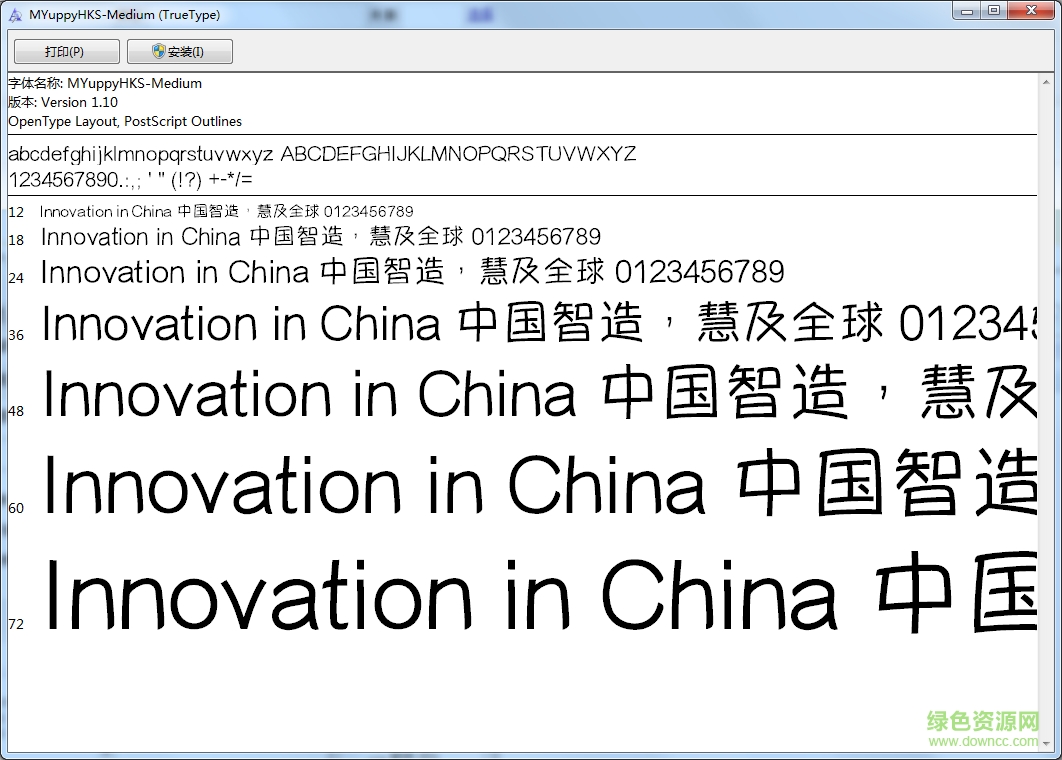
蒙納優(yōu)皮字體
蒙納優(yōu)皮體ttf是一款非常好看的字體,略帶圓圓的字體感覺,有濃濃的卡通味道,適用范圍也非常的廣,喜愛的朋友趕快到綠色資源網(wǎng)下載體驗(yàn)吧!
官方介紹
該字形帶有卡通效果,時(shí)尚大方,整體效果出眾,可以應(yīng)用于卡通設(shè)計(jì)、廣告設(shè)計(jì)、平面設(shè)計(jì)、印刷包裝、報(bào)紙雜志等行業(yè),使用時(shí)請(qǐng)選擇“MYuppyHKS-Medium”即可。